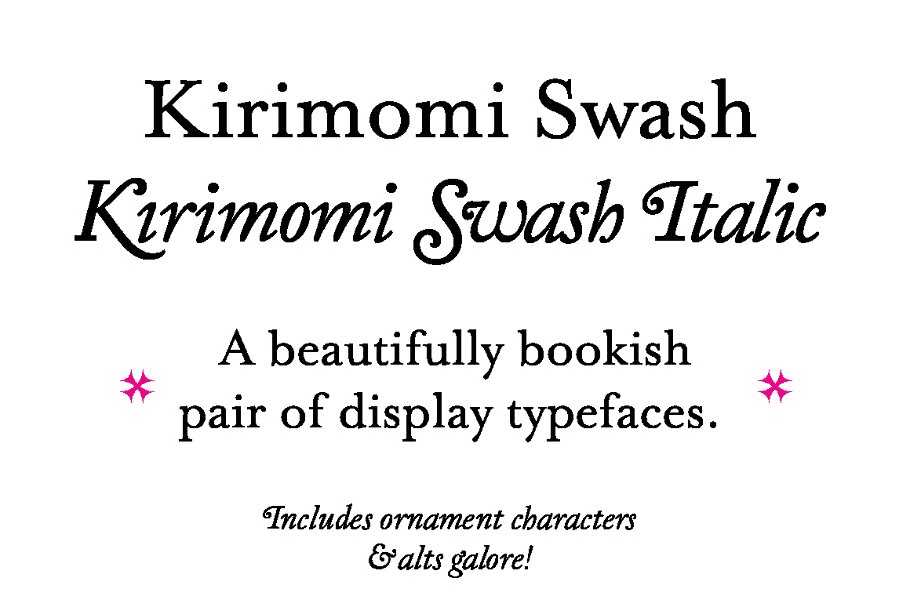
Название: Kirimomi Swash Font
Демонстрационный шрифт, корни которого уходят как в классическую форму, так и в острые грани фотоайпа. В основе шрифта лежат исторические формы французского шрифтовика Жана Жаннона, а также изогнутые клеммы и увесистые засечки работы Уильяма Каслона. Различные интерпретации их работ на протяжении всей истории были использованы для придания каждой форме букв присутствия, стабильности и жесткости. Резкие фототипические штрихи, взятые из логотипа Emperor, линии обуви для гольфа, выпущенной Onitsuka Tiger тридцать с лишним лет назад, были использованы для придания лицу актуальности эпохи модерна/постмодерна, компенсируя исторический скелетный каркас.
Kirimomi Swash - это, прежде всего, дисплейное лицо, и для того, чтобы оно функционировало изящно, в него включен ряд лигатур и альтернативных символов. Он намеренно не предназначен для набора текста, поскольку это потребовало бы сглаживания наиболее заметных элементов, и в результате, скорее всего, получился бы шрифт, который хотя и может быть полезным, но не будет выделяться в толпе.